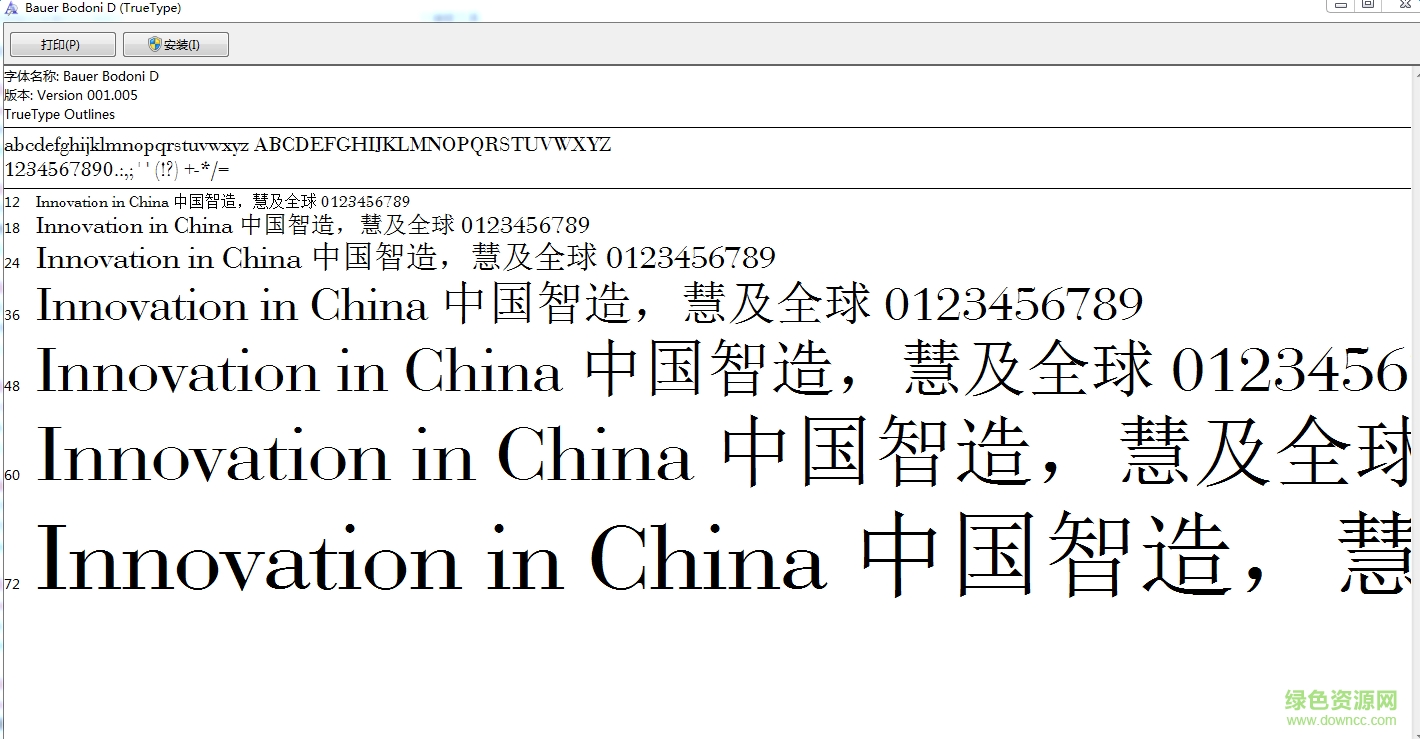
bauer bodoni字體是一款漂亮的英文字體,字形清晰飽滿,線流暢灑脫,正不拘謹(jǐn),清勁豐肥,常用于商業(yè)領(lǐng)域,有需要者歡迎在綠色資源網(wǎng)下載!
bauer bodoni字體襯線筆畫自然,粗細(xì)變化強(qiáng)烈,平整規(guī)范,視覺沖擊力顯著,非常具有現(xiàn)代感!